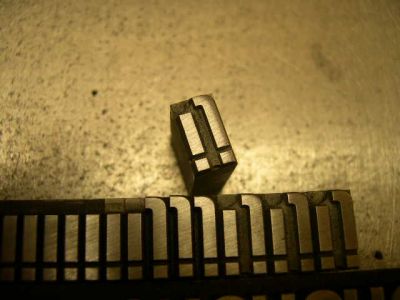
Ligaturen gibt's.. die gibt's eigentlich gar nicht
Helvetica halbfett, 36 p
Die originalen Ligaturen der Helvetica:
ch, ck, ff, fi, fl - fertig, das war's.
Heute habe ich tatsächlich eine Ligatur ij
beim Auspacken gefunden. Das ist unglaublich. Nicht sehr wichtig, aber unglaublich.
Daß es in digitalisierten Fonts zum Teil einen erweiterten Ligaturen-Satz gibt, ist mir bekannt. Oder auch, wegen der früheren Begrenzung im Zeichensatz, wie ich gelernt habe, auch oft einen abgespeckten Ligaturen-Satz - siehe die Schrift "Reporter".
Ich habe auch schon des öfteren in Bleisatz-Schriften Bleisatz Ligaturen wie z.B. "sch" gefunden, die manuell nach hergestellten Klischees nachgegossen worden waren. Aber das hier ist ein Original-Guß, gar keine Frage. Der Rheinländer kommentiert so etwas dann mit einem beiläufigen: "Wat et all' jibt.."
Heute habe ich tatsächlich eine Ligatur ij
beim Auspacken gefunden. Das ist unglaublich. Nicht sehr wichtig, aber unglaublich.
Wohl eine holländische Erweiterung, dort ist das ij ja ein eigener Buchstabe der (ich hoffe ich lüge jetzt nicht*) ganz normal in der Aufzählung der Buchstaben vorkommt.
Ha! Sehr gute Erklärung. Das wird's sein.
Diese Setzerei kam aus Wetzlar. Das hätte ich eher von der nächsten erwartet, die wir in den nächsten zwei Wochen in Emmerich abholen.
Logisch: D. Stempel hat auch jetzt noch ausländische Zeichensätze für die gängigsten Schriften. Und das hier war für einen niederländischen Zeichensatz. Jetzt, wo Du's sagst: Da waren auch Angstroem-Lettern dabei, vielleicht für skandinavischen Satz.
ich muss dich korrigieren. Robertmichael hat
Recht. Die »Georgia« hat ij-Ligaturen. Schau:
Richtig. Wie Sebastian schon schrieb.
Ich war wohl der einzige, der das nicht wußte.
Obwohl ich hier 20 Minuten Autofahrt von Venlo wohne..